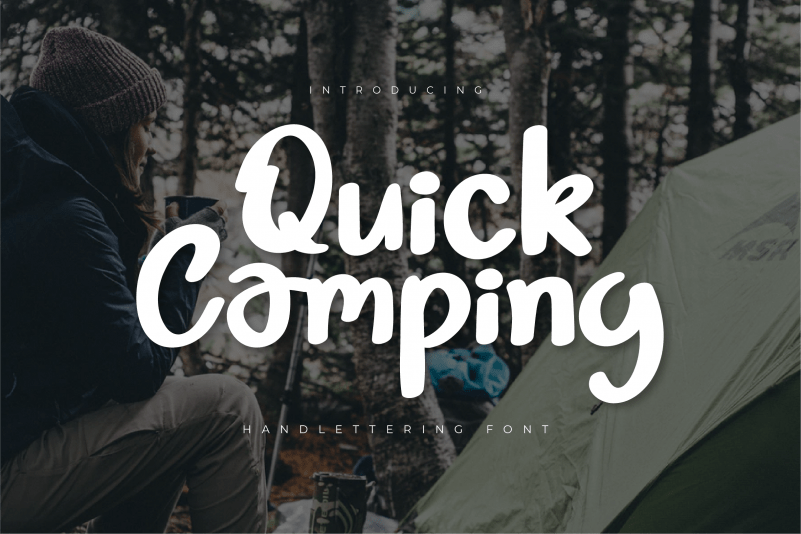
Quick Camping Script Font
A Quick Camping Script Font é uma elegante fonte feita à mão que transborda de autenticidade e serenidade. Perfeita para projetos personais e profissionais, esta fonte vem com um toque delicado que a torna única e versátil ao mesmo tempo. Suas formas fluidas e fluidas se movem como se fossem escritas à mão por alguém experiente, criando designs incrivelmente distintos e cheios de estilo único. Se apaixone por sua essência singular e eterna, já que ela está disponível para criar designs surpreendentemente bonitos e atraentes. Descubra o seu verdadeiro eu através desta fonte única, ideal para quem busca algo diferente no mundo das letras digitais.